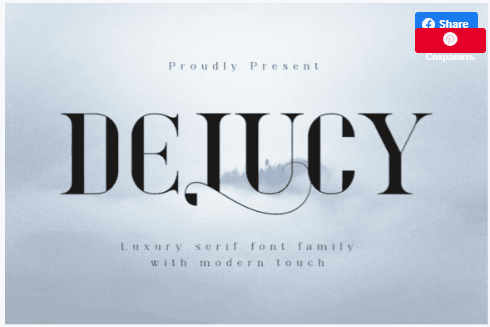
Delucy Font
Delucy - роскошный и уникальный шрифт с засечками. Этот шрифт имеет кодировку PUA, что означает, что вы можете легко получить доступ ко всем глифам и росчеркам! Влюбитесь в универсальный стиль Delucy и используйте его для создания впечатляющих дизайнов!